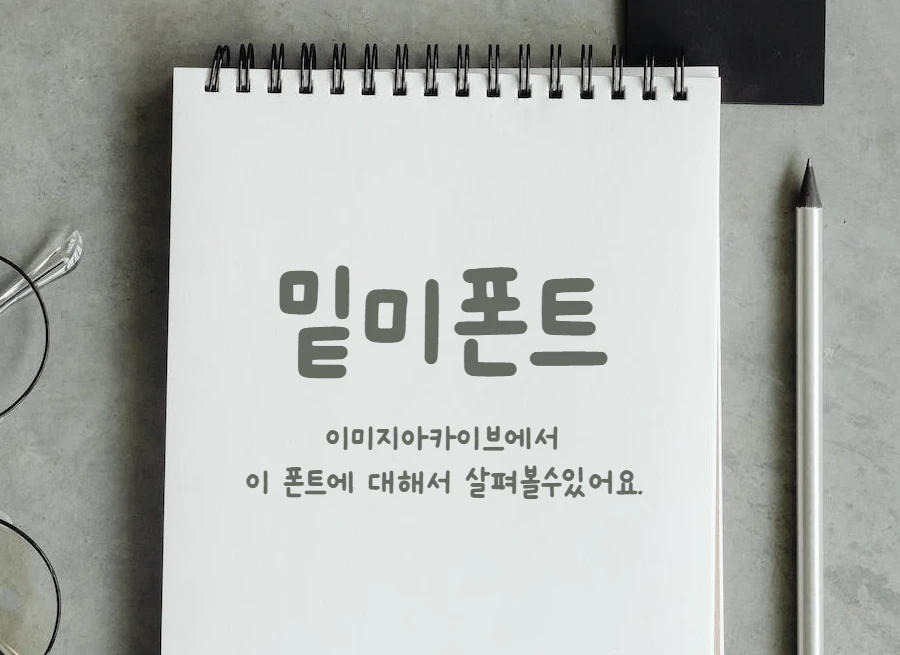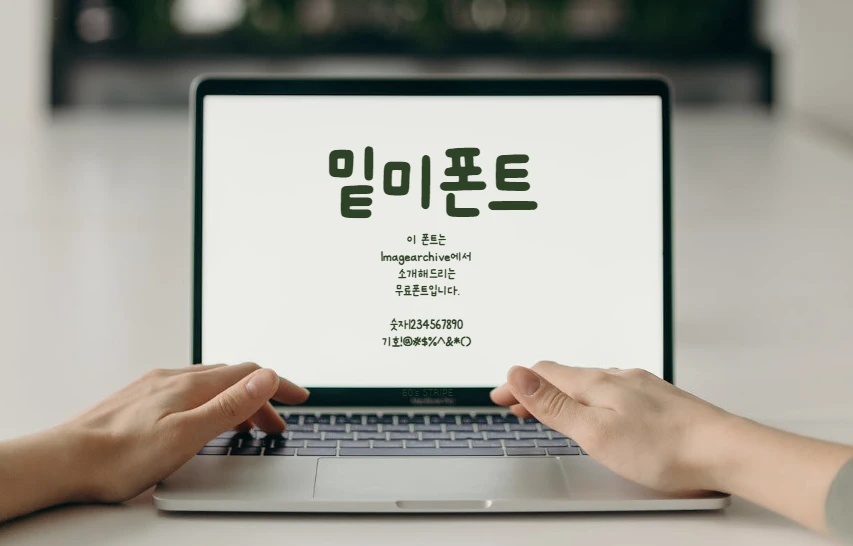
밑미폰트 Meetme
안녕하세요! 밑미팀 디자이너 루시예요. 밑미레터나 이미지에 쓰는 폰트 관련한 질문을 종종 받곤 해요. 대부분의 글씨는 손으로 쓴답니다! 활자에 사람 냄새나는 밑미의 목소리를 담고 싶기도 하고, 리드미컬하게 문장이 읽혔으면 좋겠다는 마음을 눌러담아 손글씨를 쓰고 있어요. 하지만 많은 양의 문장이 필요하거나 제가 자리를 비우는 경우에는 손으로 쓸 수 없으니, 인공지능으로 제작한 밑미 폰트의 힘을 빌린답니다!
밑미 폰트는 직접 쓰는 것보다 문장이 단정하게 읽히지만, 손글씨 특유의 느낌을 잃지 않아서 다양한 곳에 사용할 수 있어요. 더 다양한 목소리를 담고 싶어서 밑미에서만 사용하던 밑미 폰트를 이제 여러분과 나누려해요! 리추얼을 기록물로 만들고 싶을 때, 내 기록에 활기를 더하고 싶을 때 자유롭게 사용해주시면 좋겠어요.